好吧,不用再猶豫了,因為在這篇博文中,我們將深入探討馬戲字體的世界以及它們如何改變您的項目。
現在,您可能會想,“馬戲團字體? 真的嗎?” 相信我,我一開始也有同樣的反應。 但讓我告訴你,這些字體不是典型的帶有小丑和大頂帳篷的馬戲團主題字體。
馬戲團字體是一種獨特且引人注目的排版風格,可以為任何設計增添俏皮和異想天開的感覺。
在本文中,我們將探討不同類型的馬戲團字體、它們的歷史,以及如何使用它們來創建令人驚嘆的視覺效果。
我們還將分享一些有關馬戲團字體對設計項目影響的有趣統計數據和事實。 因此,如果您準備好讓您的設計脫穎而出,那麼讓我們開始吧!
最佳高級馬戲團字體
您是一名平面設計師,希望為您的設計增添一絲異想天開的魅力嗎? 我們最好的優質馬戲團字體系列就是您的最佳選擇。
這些字體將為您的項目帶來俏皮和懷舊的氛圍。 不要錯過為您的下一個項目尋找完美字體的機會。
馬戲團怪胎
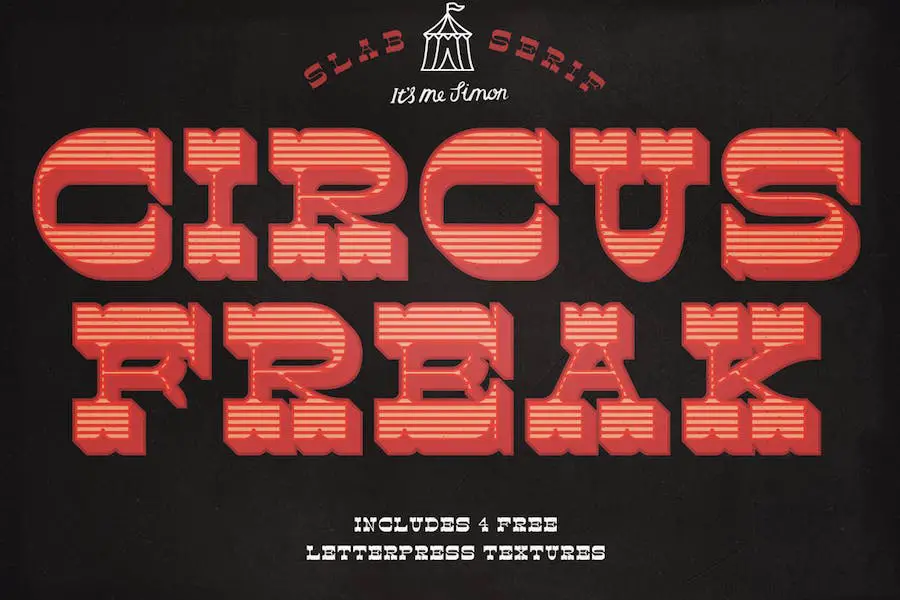
Circus Freak 是一款令人驚嘆的字體,為您的項目提供獨特且引人注目的設計。 憑藉其四種多功能樣式,您可以將它們層疊在一起,以獲得類似於復古凸版印刷的令人驚嘆的彩色效果。
這些風格包括大膽且引人注目的 Circus Freak Shadow、經典的 Circus Freak Regular、複雜的 Circus Freak Lines 和動感的 Circus Freak Shadow Stroke。
Circus Freak 的與眾不同之處在於它的靈感來自 1800 年代末的古老美國彩色木字體。 這款 Google Circus 字體可讓您為您的設計帶來一絲懷舊和復古魅力,同時增添現代氣息。
雜技演員
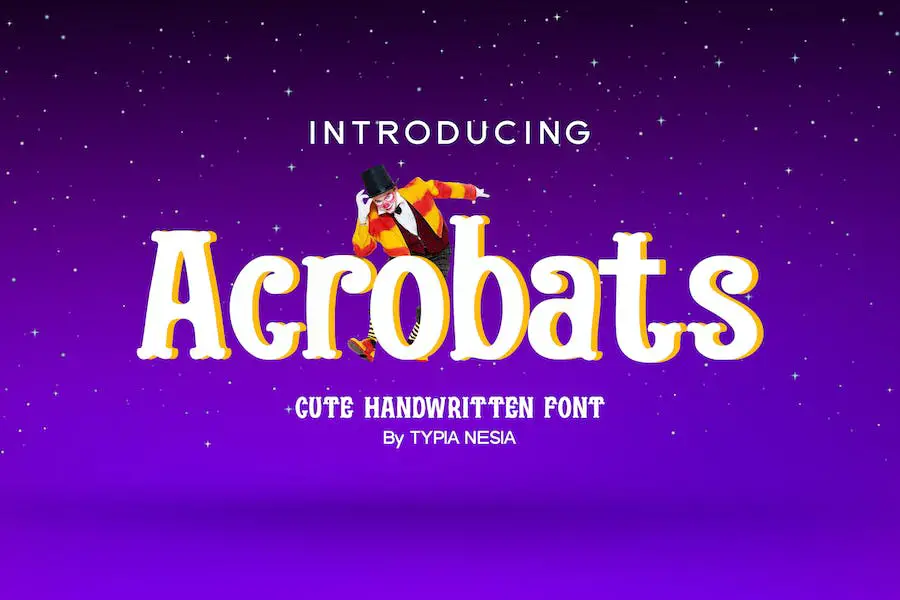
Acrobats 是一款必備的 Circus Display 字體,可以將您的設計項目提升到一個新的水平。 無論您是在設計徽標、品牌、編輯設計、文具設計、博客設計還是現代廣告,這種字體都會增添一絲創造力和獨特性。
它也非常適合卡片邀請函、藝術名言、家居裝飾、書籍/封面標題以及婚禮和生日等特殊活動。
這款 Adobe Circus 字體憑藉其大膽且引人注目的設計,在人群中脫穎而出並吸引了人們的注意。
它為您的項目帶來俏皮活潑的氛圍,立即吸引觀眾的注意力。 該字體非常適合需要一絲奇思妙想和樂趣的項目,增添一絲興奮和驚奇。
Acrobats 的與眾不同之處在於它的多功能性。 它無縫適應各種風格和主題,讓您創造不同的心情和氛圍。
無論您想要復古馬戲團外觀、現代時尚美學還是介於兩者之間的外觀,這款字體都能滿足您的需求。 它為每一個設計增添了個性和魅力,令人難以抗拒。
馬戲團
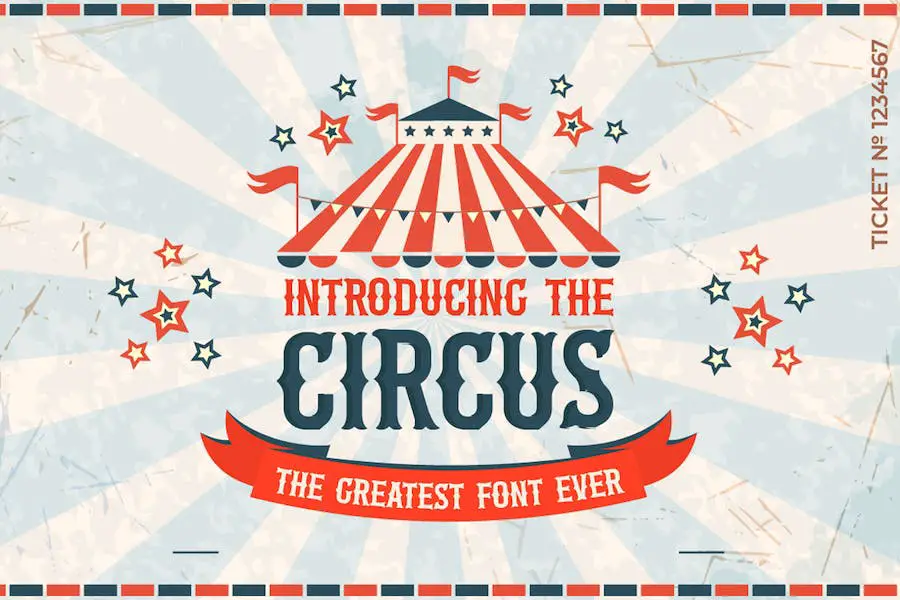
Circus 字體可以為您的設計項目帶來一絲奇思妙想和興奮。 憑藉其俏皮而古怪的風格,這種字體非常適合希望為其作品添加獨特且引人注目的元素的圖形設計師。
無論您是設計網站、創建社交媒體圖形,還是從事數字營銷活動,The Circus 都能滿足您的需求。
馬戲團
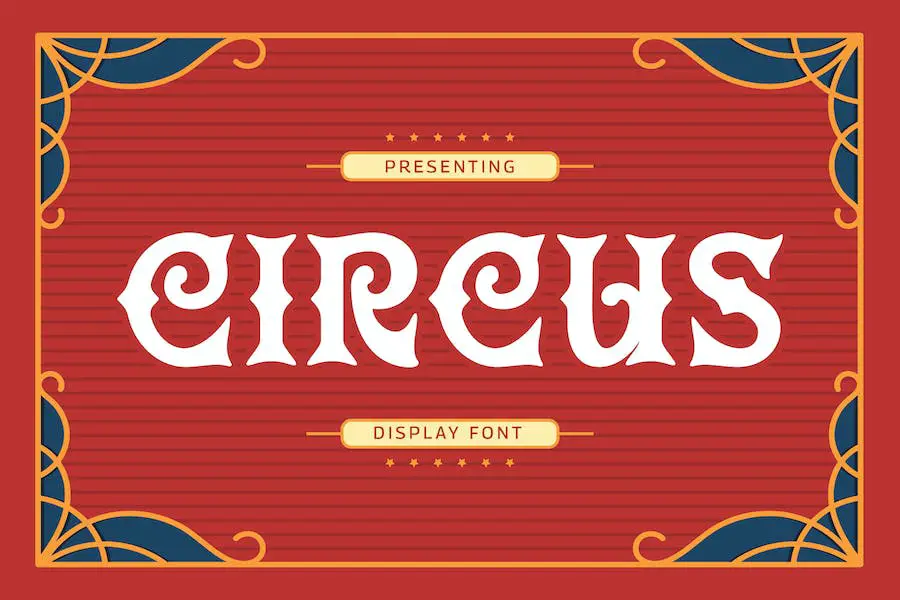
Circus 是一種提供大寫和小寫字母以及數字和標點符號的字體。
它是一種多功能字體,可以增強各種項目的設計,例如徽標、攝影設計、邀請函、水印、廣告、產品設計、文具、婚禮設計、標籤、產品包裝和特別活動。
Circus 的突出特點之一是它的多語言支持,這意味著您可以將此字體用於不同語言的項目。 如果您有來自不同文化背景的客戶或顧客,這尤其有幫助。
這款 Canva 字體的 Circus 字體非常適合那些正在尋找一種方法來提升其項目並賦予其獨特且引人注目的觸感的圖形設計師。
它的大寫和小寫字母以及數字和標點符號為設計不同類型的內容提供了靈活性和創造力。
最偉大的馬戲團
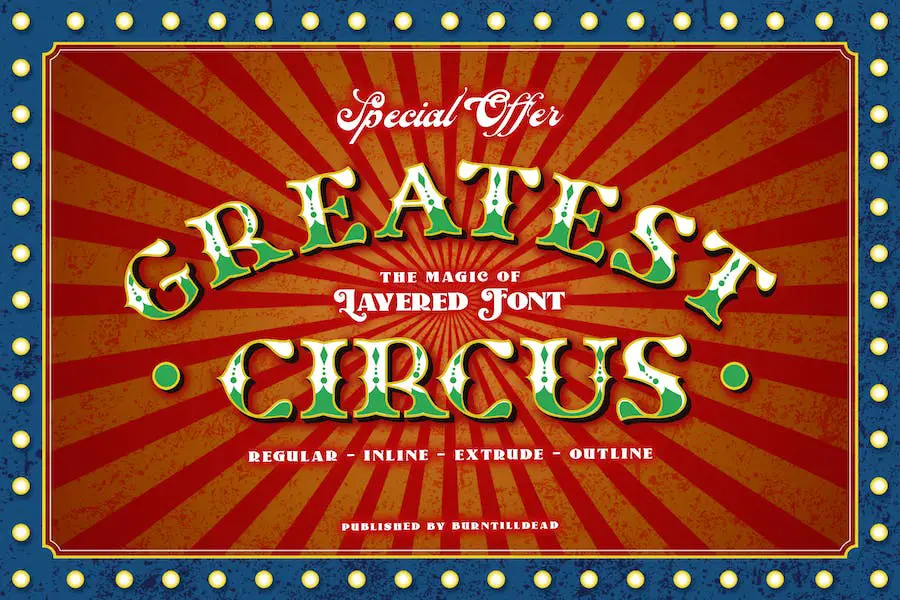
Greatest Circus 字體是平面設計師的必備之選,他們希望通過經典的美國氛圍來提升他們的項目。
受標誌性馬戲團標誌的啟發,該字體具有四種不同的樣式 - 常規、輪廓、拉伸和內聯 - 可以將它們分層在一起以創建有趣且引人注目的效果。
無論您是為嘉年華、音樂活動、魔術師表演,還是賭場徽標進行設計,Greatest Circus 字體一定會為您的作品增添有趣和充滿活力的元素。 它的多功能性使其成為任何娛樂或有趣的活動標誌或廣告的絕佳選擇。
這款用於 cricut 的 Circus 字體的分層系統允許您嘗試和嘗試不同的組合,讓您可以自由地創建真正獨特且迷人的設計。
通過將每種風格結合在一起,您可以實現動態且具有視覺吸引力的結果,立即吸引觀眾的注意力。
守護者馬戲團
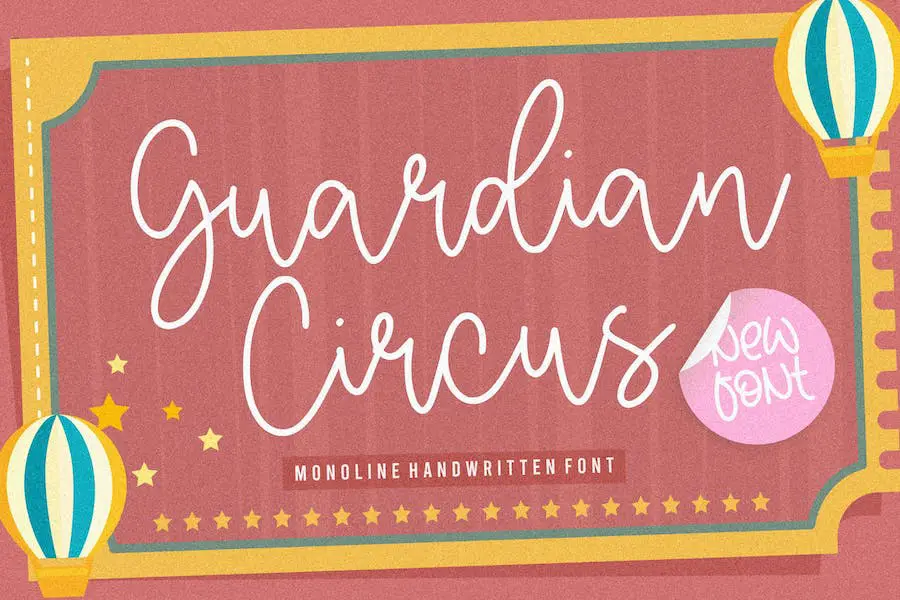
Guardian Circus 是一款出色的字體,肯定會提升任何項目的設計。 憑藉其獨特的馬戲團風格,這種字體是希望為他們的作品增添一絲奇思妙想和懷舊氣息的平面設計師的最愛。
守護者馬戲團的屬性確實令人印象深刻。 首先,它具有廣泛的用途,使其成為滿足各種設計需求的多功能選擇。
無論您是在設計產品包裝、品牌材料、雜誌佈局、社交媒體圖形,甚至是婚禮請柬,Guardian Circus 都能滿足您的需求。
馬戲表演
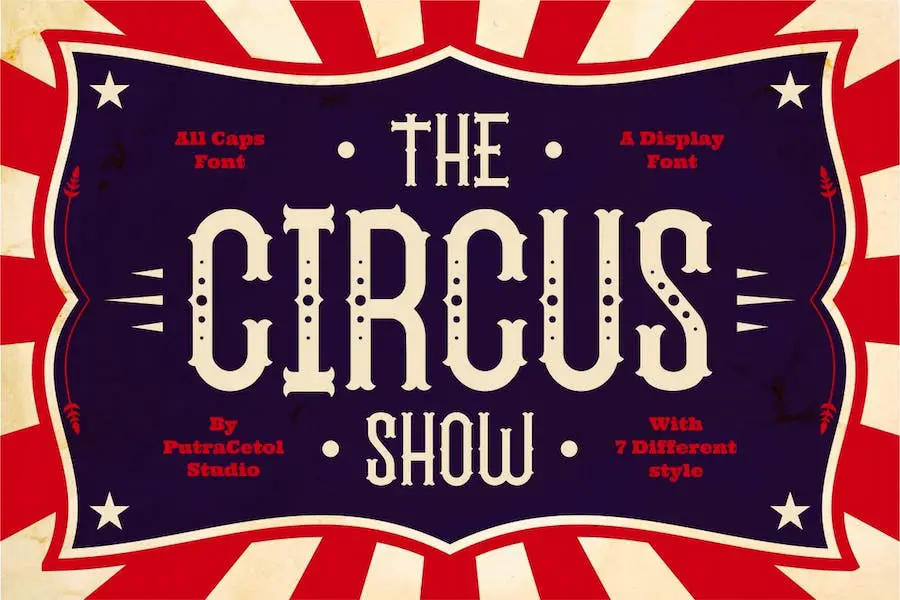
馬戲團表演是一款出色的顯示字體,其靈感來自美國馬戲團和嘉年華排版以及 80 年代的紋身。
Circus Fonts 擁有 7 種獨特的樣式,包括常規、點、中心點、線、針、粗和輪廓,非常適合創建充滿樂趣的設計。
無論您是要創建醒目的標識、引人注目的海報還是引人注目的社交媒體帖子,馬戲表演一定會讓您的項目脫穎而出。
它也非常適合標題、商品、賀卡等。 用這種令人難以置信的字體擁抱馬戲團的俏皮和充滿活力的氛圍。
皇家博格
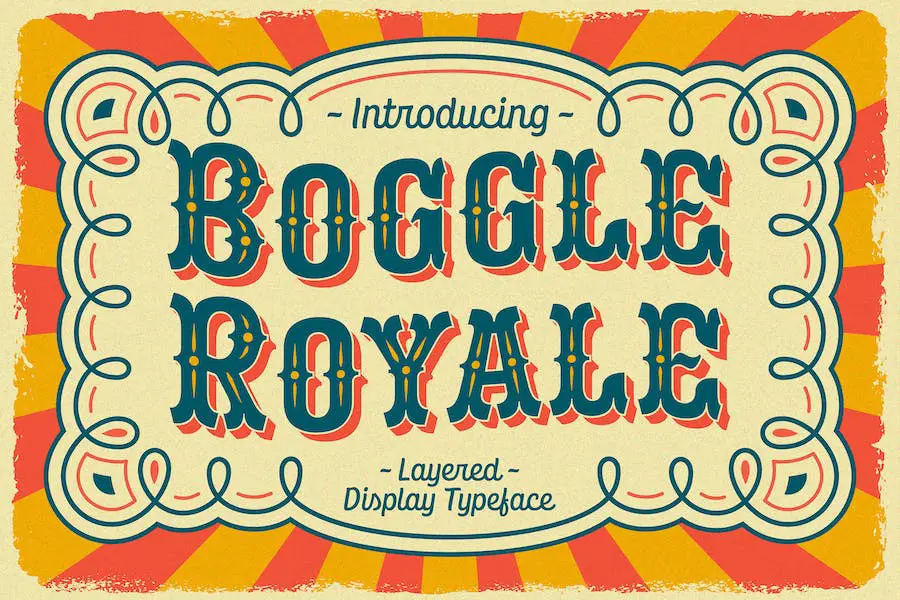
Boggle Royale 是一款出色的字體,非常適合為您的設計項目增添一絲樂趣和獨特性。 憑藉其複古馬戲團和節日靈感的設計,這種字體一定會讓您的徽標、邀請函、雜誌、書籍和包裝脫穎而出。
該字體具有三種變體——常規、陰影和陰影——讓您可以自由地嘗試和創建更詳細的設計。
無論您想要大膽而充滿活力的外觀還是更加微妙和有質感的效果,Boggle Royale 都能滿足您的需求。
瑟庫西蒂
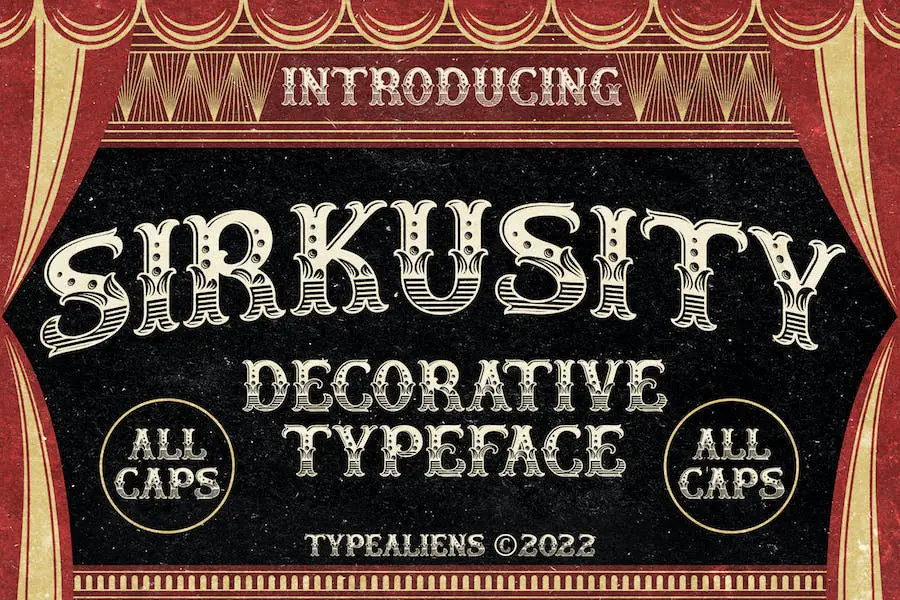
Sirkusity 是一種屬於高度裝飾性類別的顯示字體,具有迷人的馬戲風格主題。
憑藉其複古魅力,這種字體是創建真正捕捉活動精髓的複古風格馬戲海報的完美選擇。
Sirkusity 專為馬戲團類型的設計而定制,使其成為一種高度專業化和細分的字體。 它完全由大寫字母組成,為您的設計增添了額外的影響力和大膽感。
巴爾小丑
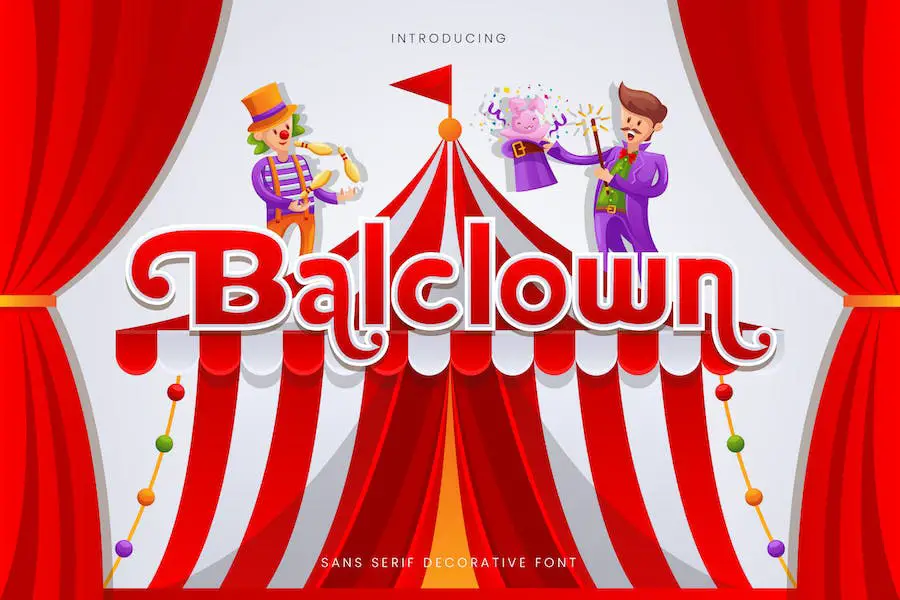
Balclown 字體是想要為項目添加一絲樂趣和可愛的圖形設計師的完美選擇。
這種大膽俏皮的字體專為兒童相關場合而設計,為任何設計帶來可愛的魅力。
卡尼庫斯
Carnicus 是一種獨特而強大的字體,允許圖形設計師通過非凡的排版和字體來增強他們的項目。
憑藉其馬戲團靈感的設計,該字體非常適合徽標、標題、標題、印刷品和其他創意過程。 無論您是設計海報、品牌項目還是網站,Carnicus 都會將您的設計提升到一個新的水平。
Carnicus 的突出特點之一是它的多功能性。 這種字體類型為希望為其項目添加俏皮和異想天開的感覺的設計師提供了無限的創意可能性。
其大膽而引人注目的風格使其非常適合吸引觀眾的注意力並創造令人難忘的視覺衝擊力。
桑多里安
Sandorian是一種具有復古風格的多層字體。 它提供 6 層,可以組合起來創建獨特且引人注目的字體。
Sandorian 非常適合模板、宣傳冊設計、視頻、品牌和徽標等設計項目,是希望提升項目水平的平面設計師的多功能選擇。
憑藉其複古風格的美學,這種字體為任何設計增添了一絲懷舊和個性。 Sandorian 發揮創意,讓您的項目脫穎而出。
夢幻島
Neverland 是一款令人驚嘆的字體,其靈感來自複古奇幻電影海報和經典圖畫小說封面。 對於想要通過一點點奇思妙想和想像力來增強他們的項目的圖形設計師來說,它是完美的選擇。
該字體有兩種獨特的樣式可供選擇 - 陰影或常規 - 該字體可讓您為您的設計創造令人印象深刻的環境。
無論您是想喚起愛麗絲夢遊仙境的魅力、綠野仙踪的魔力,還是納尼亞的奇幻世界,夢幻島都會將您的史詩般的想法變為現實。
喬克
Jocker – Vintage Serif Font Family 是一種 8 層襯線風格顯示字體。 它是對複古美國和歐洲粗體無襯線字體在廣告管理方面的探索的結果。
這種有吸引力的現代字體是從頭開始繪製的,具有全新的、更有活力的細節。 另外,它還提供了可分層的色彩使用變化。
Jocker 不是普通的襯線字體。 憑藉其複古風格和大膽,它為您的設計項目帶來一絲懷舊之情。 無論您是在製作復古風格的海報、復古標誌還是引人注目的廣告,這種字體一定會引起人們的注意。
Jocker 的魅力在於它的多功能性。 它有 8 層,讓您可以嘗試並創造令人驚嘆的色彩效果
德霍爾斯
Dehors 是一種西方顯示字體,可為您的設計項目增添經典的西方風格。 它非常適合創建引人注目的徽標、邀請函、標籤、雜誌佈局、書籍、賀卡、包裝等。
憑藉其多功能且優雅的設計,Dehors 是任何類型的廣告或促銷材料的理想選擇。
無論您是在參與時尚活動、化妝品品牌,還是只是需要提升您的文具,Dehors 字體都能將您的設計提升到一個新的水平。
弗瑞斯
Furius 是一種獨特的顯示字體,其靈感來自於古羅馬銘文和西方流派中木刻或鑿刻字母的分體襯線風格。
您可以在各種創意項目中使用馬戲團字體。 它們非常適合主題派對和活動、兒童生日邀請、馬戲主題網站以及馬戲相關企業或娛樂場所的品牌推廣。
此外,馬戲團字體可以為複古風格的設計項目增添俏皮感。
結論
在本文中,我們討論了馬戲團字體的使用以及它們如何改進項目的設計。
我們探索了這些有趣且充滿活力的字體的不同風格和特徵,以及它們如何為您的設計增添一絲奇思妙想和興奮。 無論您是在製作海報、徽標還是任何其他設計項目,馬戲團字體都絕對可以彰顯個性。